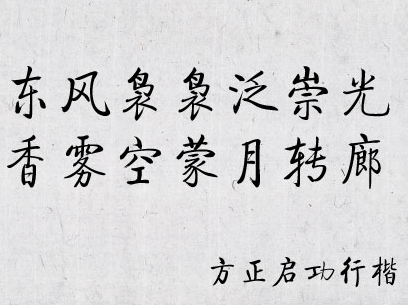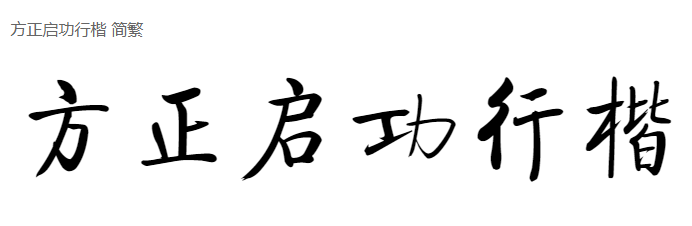
方正启功行楷简繁
方正启功行楷
品牌: 中华精品书法字库
设计师: 秦永龙
字体介绍:
启功(1912-2005),当代书画家、书画鉴定家、文史学家。字元伯,一作元白,满族,生于北京。长期从事文史教学与研究,曾任教辅仁大学,新中国成立后任北京师范大学教授、中央文史研究馆馆长、中国书法家协会主席等职。精于书画及文物鉴定,任国家文物鉴定委员会主任委员。在书学上力主临习墨迹,尤其重视结字,创“黄金分割法”。书风于端庄静穆中寓劲健飘逸。著有《启功丛稿》、《论书百绝》等,并有《启功书法作品选》等多种书法结集。
字体特征:由启功先生指定北京师范大学书法教授、中国书法家协会教育委员秦永龙先生书写。结体精严,笔画清朗刚健,布势轻重有别,主宾相济,风神俊秀且雅俗共赏。个性从容清秀,体态大方,典雅遒丽,带有一股文雅的书卷气。